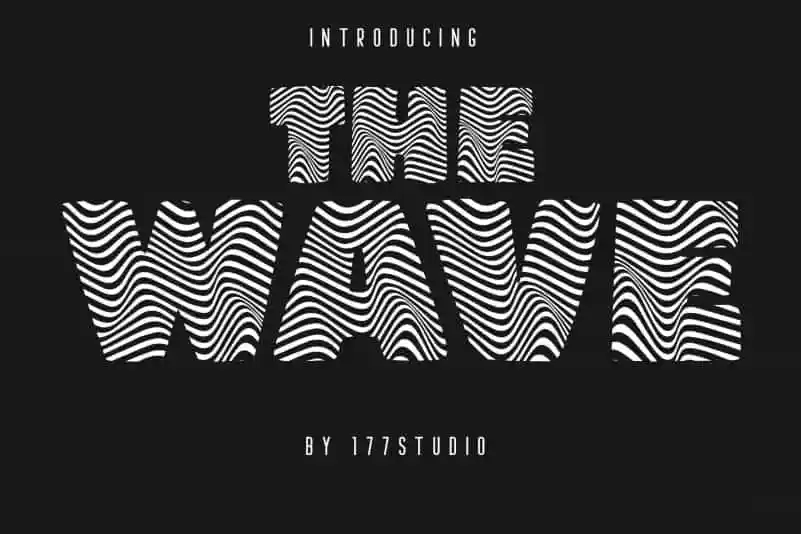
The Wave – Display Font – Download Grátis
A fonte The Wave Display Font é uma escolha única para qualquer projeto que busque um ar retrô e sofisticado. Inspirada na escrita manual de letras de chão de café, com suas linhas onduladas entrelaçadas como patamar de zebra, ela oferece um toque artístico e vibrante ao seu design. Ideal para criar uma atmosfera elegante em logotipos, adesivos ou até mesmo publicações impressas, The Wave Display Font é perfeito para quem busca uma fonte de destaque que remete a velhas mensagens esboçadas nas salas de espera dos cafés. Com seu design minimalista e sua estrutura impecável, The Wave Display não só captura o espírito dos anos 90 e início do século 21, mas também oferece uma maneira única de fazer as letras vibrarem no espaço da qual são usadas.